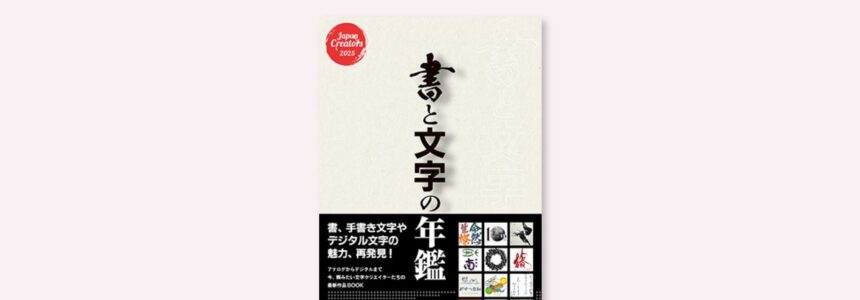
『書と文字の年鑑 2025』のご紹介
書と文字の年鑑 2025
『書と文字の年鑑 2025』は、書・筆文字・カリグラフィー・タイポグラフィー・フォント・ロゴなど、「文字」に関する多様な表現を一冊にまとめた年鑑です。
印刷物やデジタルメディアにおいて、文字が単なる情報伝達の手段ではなく、造形や感情表現としてどのように機能しているのかを丁寧に掘り下げています。
現代のデジタル環境では失われがちな“揺らぎ”や“ノイズ”といった人間的で有機的な要素に価値を見出し、それらを生かした文字表現の重要性を提起しています。
タイポグラフィやロゴ制作に関わるデザイナー、書や文字に関心のある方にとって、インスピレーションの源であり、最新の事例や潮流を把握できる実用的なリファレンスブックです。